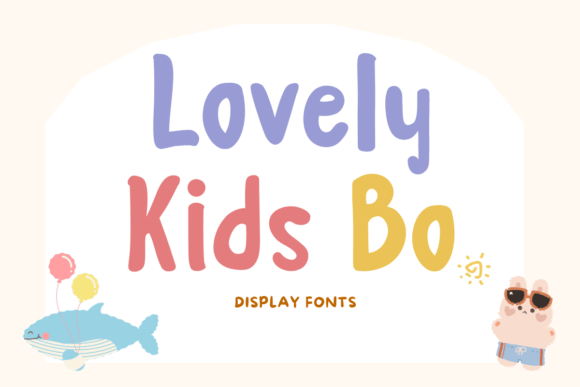
Lovely Kids Bo
Ulasan Lengkap: Lovely Kids Bo – Font yang Bersinar untuk Proyek Anak-Anak
Jika Anda sedang mencari huruf yang tidak hanya menarik tapi juga ceria dan bersahabat, Lovely Kids Bo adalah jawaban yang sempurna. Font ini dirancang dengan gaya yang playful dan cute, menampilkan bentuk huruf yang lembut dan berwarna, membuatnya sangat cocok untuk segala aplikasi yang menargetkan anak-anak atau suasana yang ringan dan menyenangkan.
- Fitur Utama: Bentuk huruf yang bulat dan lembut, ukuran yang mudah dibaca, dan variasi ketebalan yang serbaguna.
- Kompatibilitas: Cocok untuk kartu ucapan, headline, logo, poster, blog, tas, T‑shirt, pakaian, bahkan desain tema anak.
- Optimalisasi Warna: Sangat menonjol ketika dipadukan dengan warna cerah (kuning, pink, biru muda). Ini membantu elemen teks menonjol tanpa terasa terlalu berlebihan.
Dengan Lovely Kids Bo, setiap proyek yang menargetkan audiens anak-anak akan terasa lebih hidup dan mengundang senyum. Mulailah menciptakan desain yang memukau hari ini!